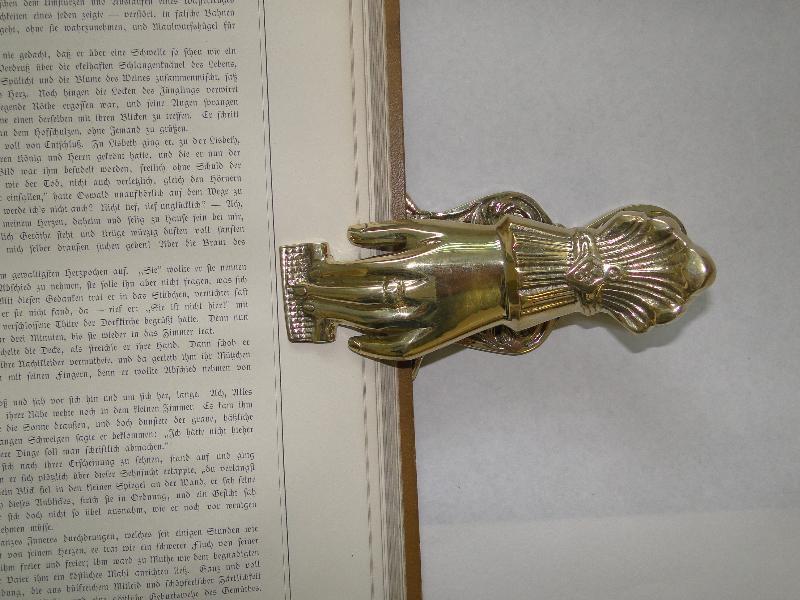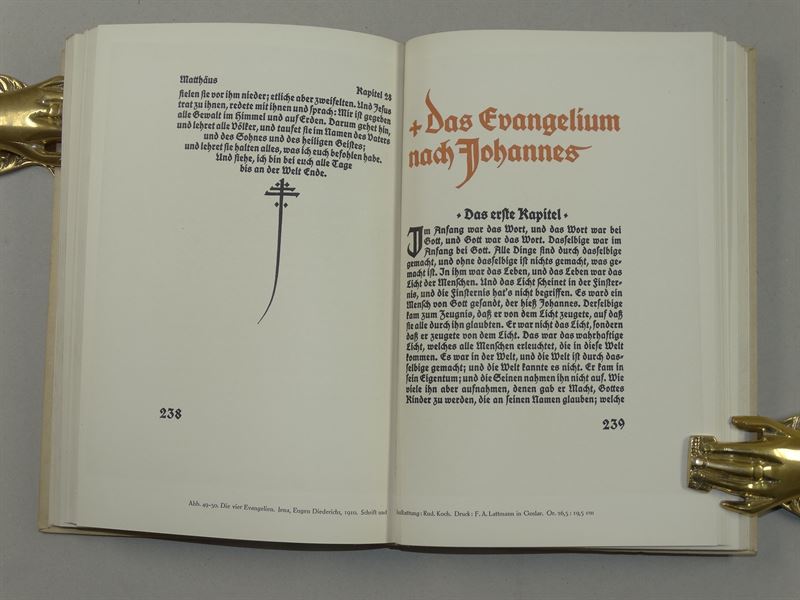
Bücher offen halten
Buchklammer. Gibt’s bei ebay.
Darf aber anscheinend nur für Bücher genutzt werden, die in Fraktur gedruckt sind.
Ist doch klar. Fraktur sind gebrochene Schriften, also nur noch Bruchstücke, Fragmente, Teile, also gaaaanz leichte Buchstabenreste ... Viel leichter als das Papier ...
Antiqua kommt von in Stein gemeißelten römischen Inschriften, das ist was ganz felsenschweres und die Bücher bleiben ob des Gewichtes der Buchstaben ganz von alleine offen! ;-)